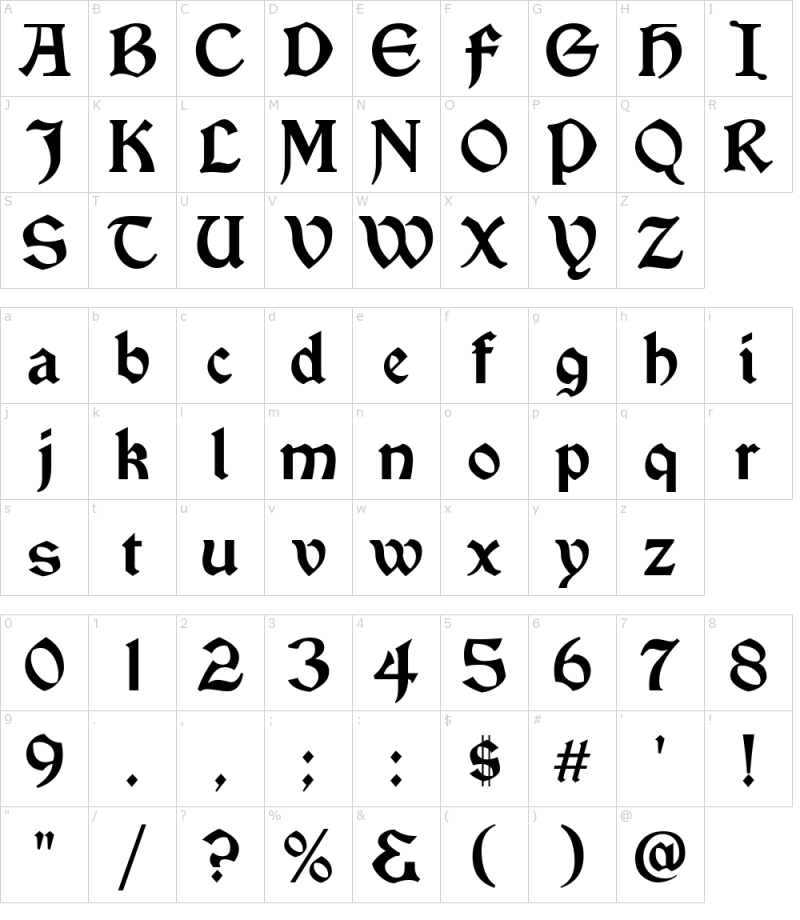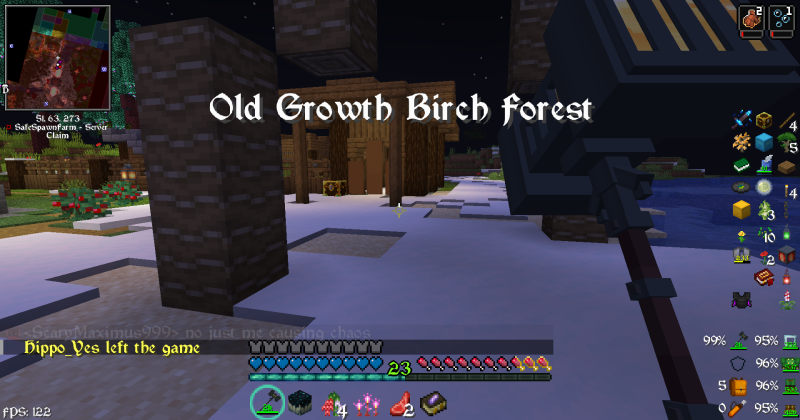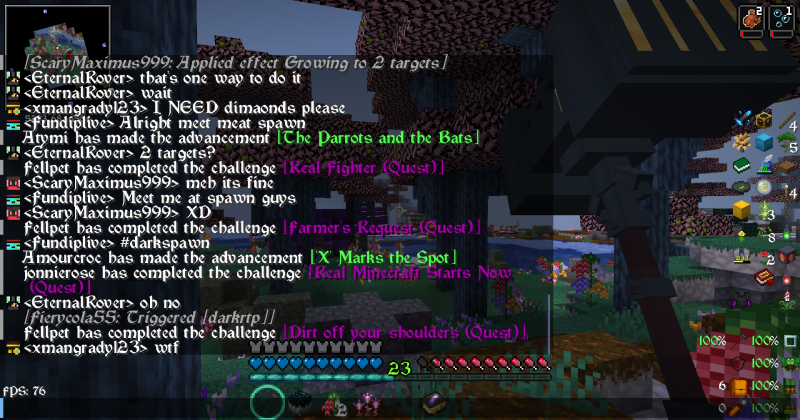
Gothic Medieval RPG Font 26.3/1.21.11 (Готический средневековый шрифт 32x)
Этот текстурпак предлагает уникальный визуальный стиль, заменяя стандартный шрифт Minecraft на готический средневековый вариант. Шрифт сохраняет чёткость и удобочитаемость, что делает его практичным для игрового процесса, одновременно добавляя атмосферу тёмного фэнтези и средневековья.
Основанный на шрифте Vinque от Typodermic Fonts, этот ресурспак лицензирован по Free Font License и изначально создавался для модпака DarkRPG, но теперь доступен всем игрокам. Он идеально подходит для ролевых игр, серверов с тёмной тематикой или просто для тех, кто хочет обновить визуальный стиль своего мира.
• Готический средневековый дизайн шрифта
• Высокая читаемость без ущерба для атмосферы
• Поддержка всех текстовых элементов игры